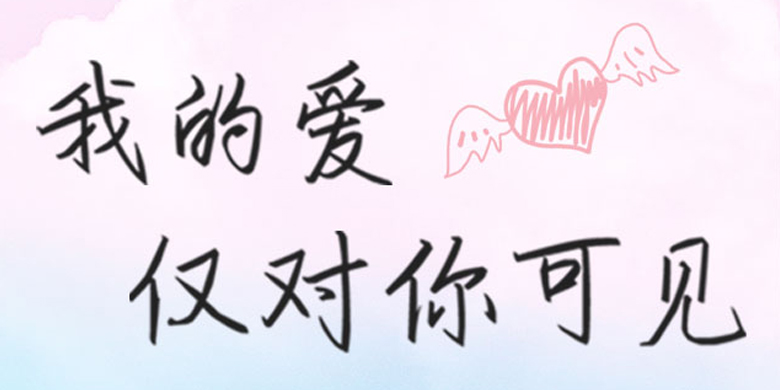
方正手迹-我的爱仅对你可见
字体品牌: 方正手迹 设计师:余丹 字体分类:创意书写 字体属性:精品字 字符集:简繁扩展(GBK) 发布时间: 2020
我的爱仅对你可见是一款文艺风格的手写体。该字体中宫收紧,笔画向外伸展,行笔流畅硬朗。适用于文艺类的书刊、品牌广告和产品包装设计,以及社交网络的个性化用字。